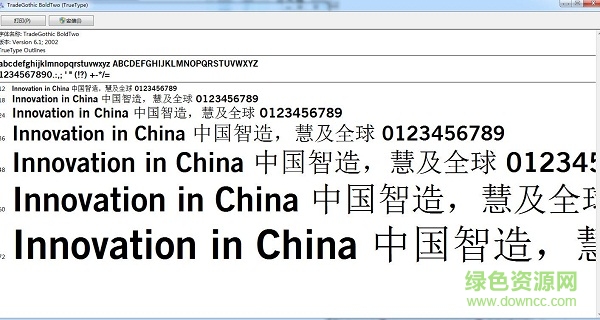
tradegothic-boldtwo字体是一款清新的无衬线字体,结构简单,没有多余的笔画,看起来大方得体,实用易读,不容易引起眼睛疲劳,喜欢的朋友快来下载吧!
最适合的正文字体应该是近似“半透明的”。一方面采用适当的衬线技巧,以提高字体在不同字号和各种阅读环境下的识别率。另一方面在字形结构上应该采用和宋体和黑体近似的字形结构,因为这种熟悉的字形,会降低识别的难度,也就是尽量不让人注意到字体本身,而是文字背后的含义。